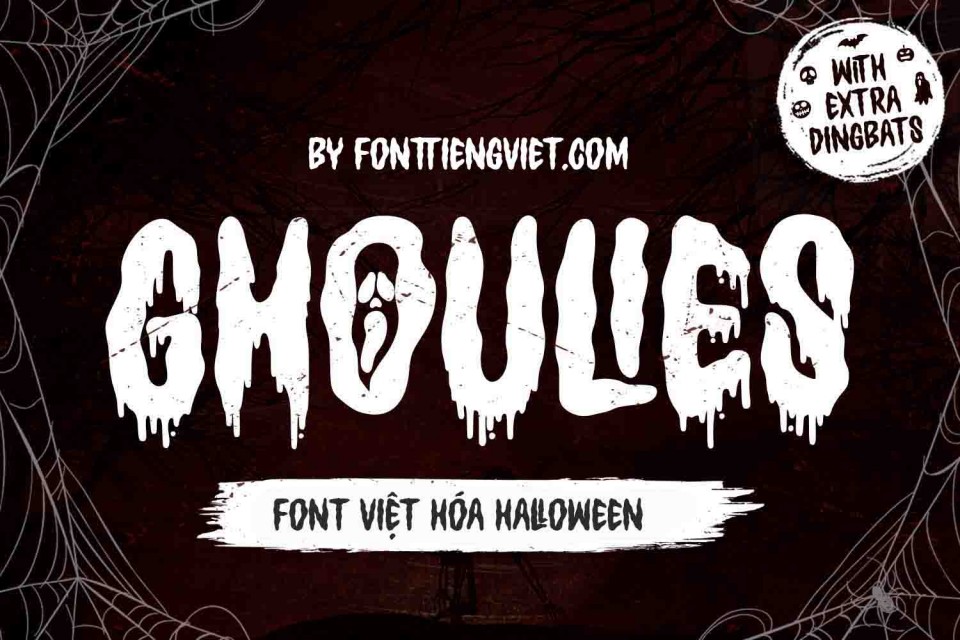
Font việt hóa 1FTV VIP Ghoulies kiểu Halloween
Tải Ngay Font việt hóa 1FTV VIP Ghoulies kiểu Halloween Độc Đáo Cho Thiết Kế Ma Mị
Chào mừng các bạn đến với thế giới sáng tạo đầy huyền bí. Trong bài viết hôm nay, chúng tôi xin giới thiệu bộ Font việt hóa 1FTV VIP Ghoulies kiểu Halloween, một lựa chọn hoàn hảo cho những dự án mang phong cách rùng rợn và lôi cuốn. Nếu bạn đang tìm kiếm một Font Miễn Phí để làm nổi bật các thiết kế sự kiện hay bài giảng chủ đề lễ hội, thì đây chính là giải pháp lý tưởng nhất. Bộ phông chữ này không chỉ giữ nguyên linh hồn của bản gốc mà còn được tối ưu hóa hoàn toàn cho ngôn ngữ Tiếng Việt, giúp các bạn sử dụng mượt mà không lo lỗi dấu.
Đặc điểm nổi bật của Font việt hóa 1FTV VIP Ghoulies kiểu Halloween
Bộ phông chữ này sở hữu những đường nét uốn lượn, mô phỏng hình ảnh các bóng ma và các yếu tố kinh dị đặc trưng. Font việt hóa 1FTV VIP Ghoulies kiểu Halloween mang đến cảm giác rung rợn nhưng vẫn giữ được sự tinh tế, phù hợp cho nhiều mục đích khác nhau.
Ứng dụng trong giáo dục và thiết kế học đường
Các thầy cô giáo và học sinh có thể sử dụng bộ phông này để trang trí bảng tin, làm thiệp mời cho các buổi tiệc Halloween tại trường. Nhờ tính năng việt hóa chuẩn, việc soạn thảo các khẩu hiệu hay tiêu đề bằng tiếng Việt trở nên chuyên nghiệp và bắt mắt hơn bao giờ hết. Hình ảnh các con chữ biến hóa linh hoạt giúp kích thích trí tưởng tượng và sự hứng thú cho các em nhỏ trong mỗi tiết học ngoại khóa.